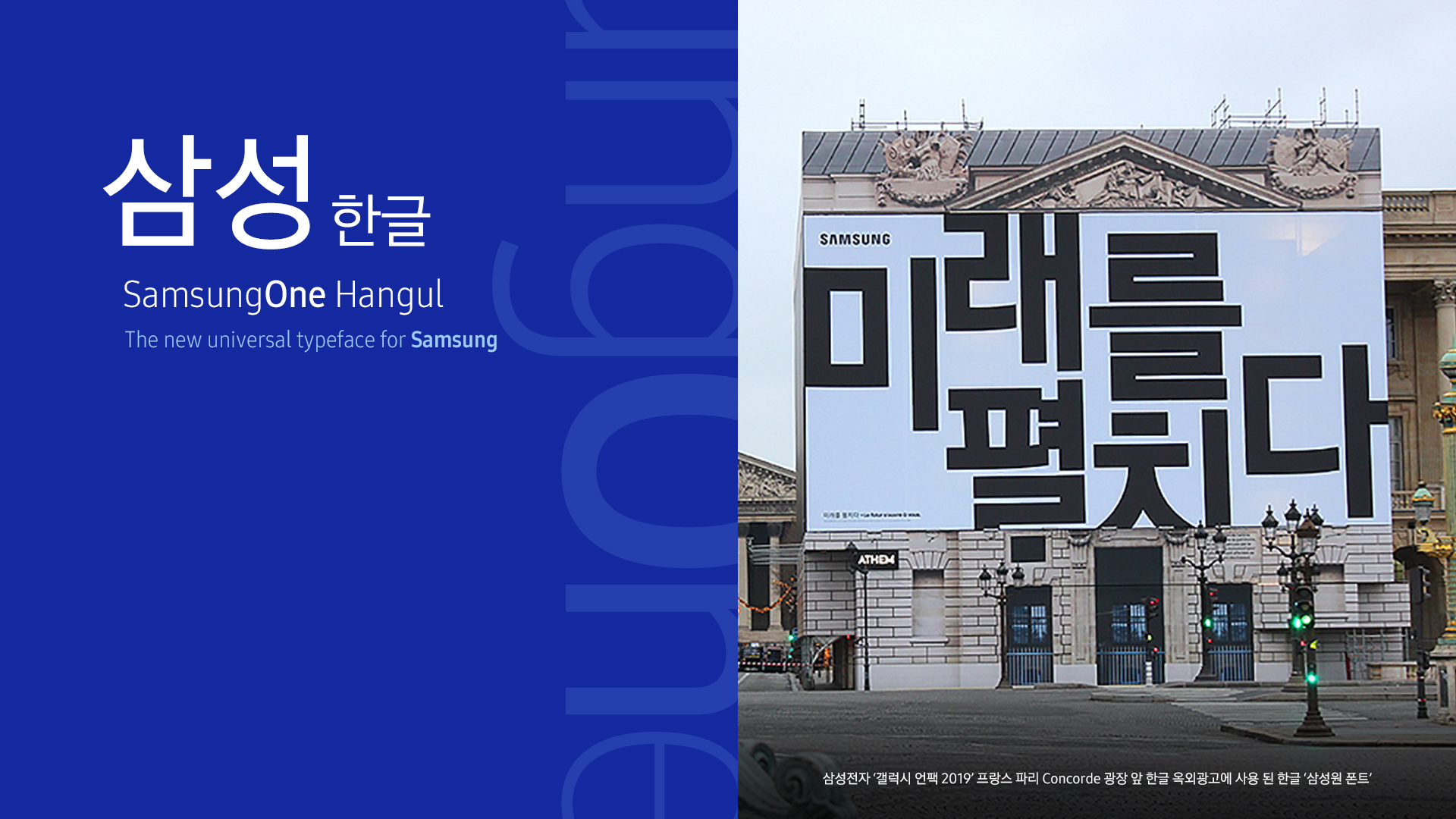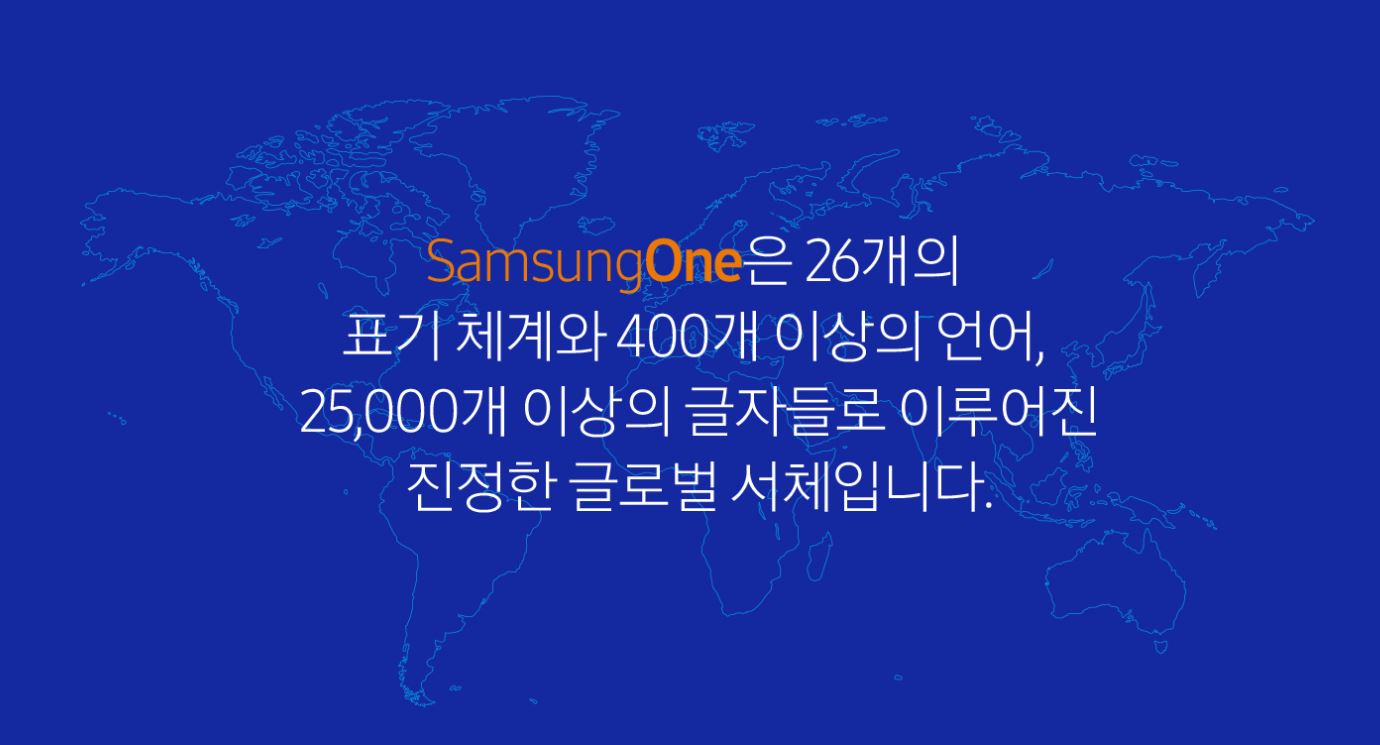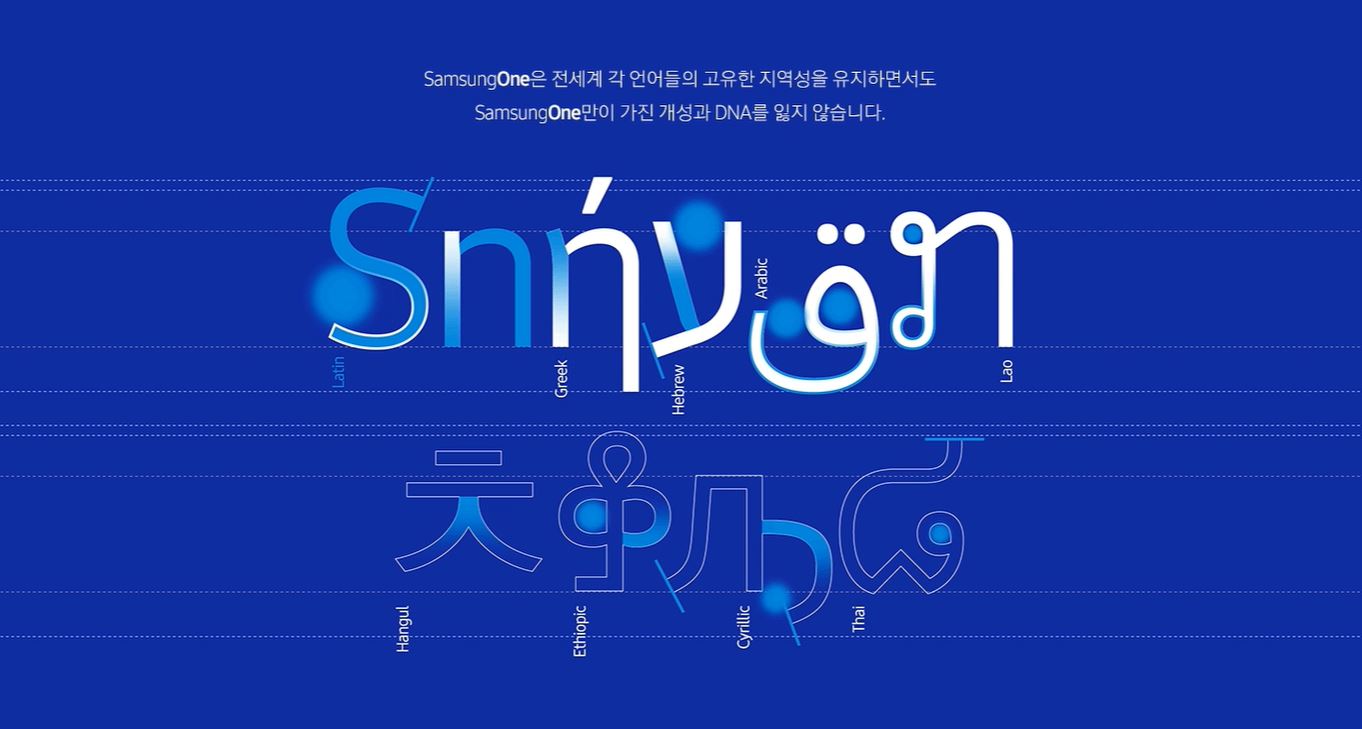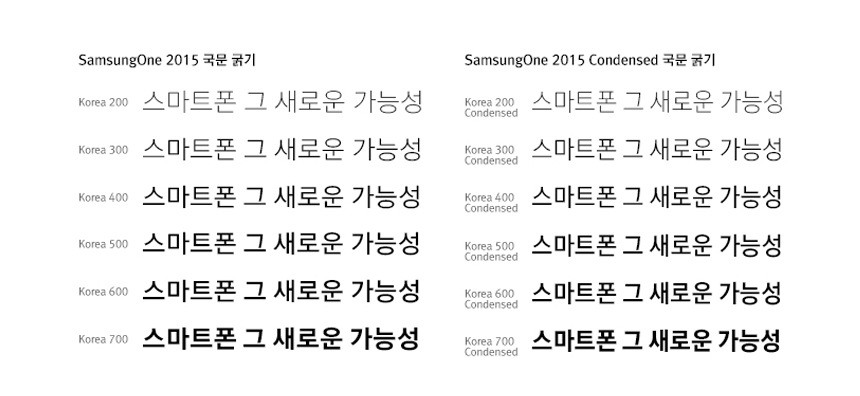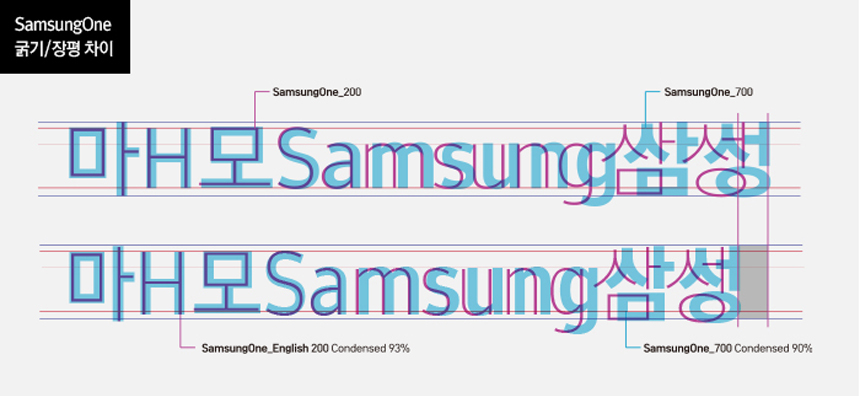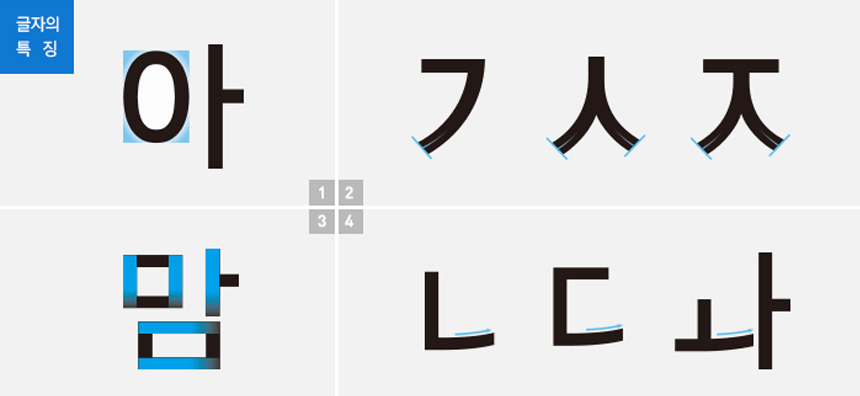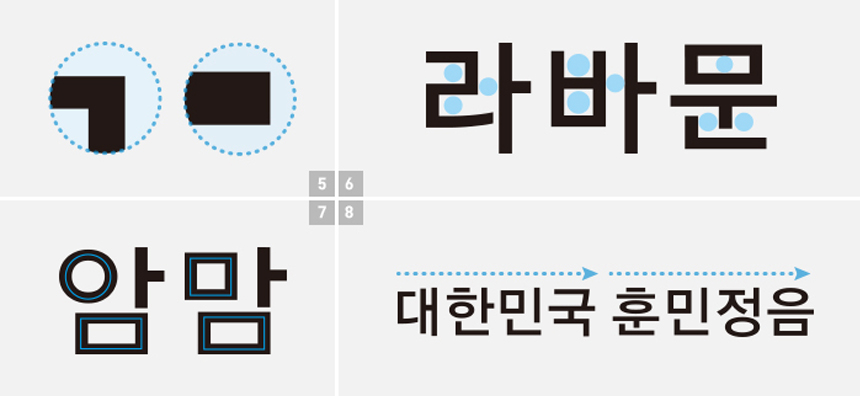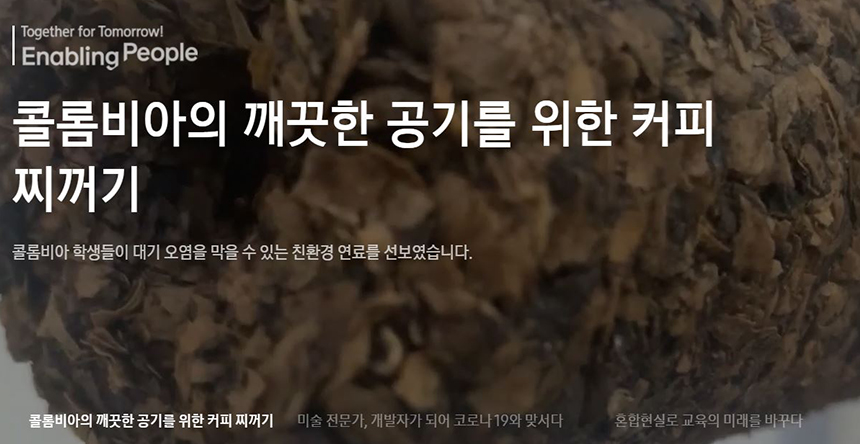
오늘 알아볼 전용서체는 대한민국을 대표하는 기업인 삼성의 전용서체 「SamsungOne」한글 입니다. 2015년부터 2018년까지 오랜 기간에 걸쳐 폰트릭스에서 개발한 삼성의 국문용 서체는 현재까지 삼성전자 전사 국문 폰트로 다양하게 사용되고 있습니다. 디스플레이, 인쇄물 등 모든 환경에서 최적화로 사용이 가능하도록 개발된 서체입니다.
글로벌 서체 SamsungOne
전용서체를 제작할 때 한글을 먼저 만드는 경우가 있고, 영문을 먼저 만든 후 그 컨셉에 맞춰 한글을 제작하는 경우가 있는데 삼성의 SamsungOneKorean 서체의 경우는 후자에 해당됩니다. 즉 영문은 해외 디자이너가 먼저 개발하고 한글은 거기에 맞춰 제작한 사례입니다. 영문의 경우 세계적인 타이포그래퍼이자 그래픽 디자이너인 네빌 브로디(Ceo, Brody Associates)가 제작하였습니다.
"중요한 것은 쓰여진 단어가 아니라 그것이 어떤 방식으로 쓰여졌느냐이다." - 네빌 브로디
'하나의 서체는 곧 하나의 시스템'이라고 말한 네빌 브로디는 수많은 제품과 플랫폼을 보유한 삼성전자를 대표하는 서체를 만들기 위해 고군분투했다고 하는데요. 특히 작은 스크린에서나 대형 옥외광고에서나 눈에 잘 띄어야 하기 때문에 스케일(크기)에 가장 중점을 두었고, 소문자 높이를 키워 가독성을 강화시킨 것이 특징입니다. 이러한 특징들이 국문 서체에서도 잘 드러나도록 디자인했습니다.
삼성원 한글 서체의 특징
SamsungOneKorean 서체는 200~900까지 총 8종(TTF/OTF)의 굵기로 파생되었고, 힌팅은 총 6종의 굵기로 파생되었습니다. Condensed(폭이 좁은)까지 제작을 진행했기 때문에 3년 이상의 긴 시간이 소요되었습니다. 국문 폰트를 담당한 박용락 디자이너는 그동안의 한글 고딕 제작 노하우를 모두 담았다고 해도 과언이 아니었다고 하는데요. 그 디테일들을 한 번 자세히 살펴보겠습니다.
활자의 완성도는 디테일에서 차이가 납니다. 글자 내 공간감을 주는 꽉 찬 곡선의 형태, 맺음 부분이 수적적인 자소, 시각적으로 같은 두께로 보이게 하는 굵기 처리, 그리고 곡선 처리가 미묘한 자소 등 세심하게 작업했습니다. 영문과 동일한 특징들을 적용해 영문, 한자와의 조화도 균형미 있게 제작되었습니다.
장식 없는 산세리프 형태로 깔끔한 이미지를 주고, 자소와 자소 사이의 간격이 균일하고 일정한 느낌을 주어 간결합니다. 한글 자음 'ㅇ', 'ㅁ'과 같이 원, 사각형으로도 보이는 기하학적인 형태를 담고 있으며, 대한민국 문서 체계에 맞게 왼쪽에서 오른쪽으로 흐르는 좌횡서 형식을 띄고 있습니다.
SamsungOne 폰트의 활용
SamsungOneKorean 서체는 삼성전자 홈페이지 및 여러 삼성의 웹사이트에서 다양하게 활용되고 있습니다. 용도에 맞게 적당한 굵기와 크기로 쓰여 높은 가독성과 함께 디스플레이에 최적화된 모습을 볼 수 있습니다.
사용성이 높은 본문형 고딕 서체이기 때문에 짧은 문구가 들어가는 광고든, 문장이 긴 콘텐츠든 여러 방면으로 활용하기에 좋습니다. 적절한 공간감을 통해 작은 글자는 서로 잘 구분되고, 큰 글자는 역동적인 느낌을 주어 임팩트 있게 표현됩니다.
기업전용서체 제작을 통해 기업의 아이덴티티와 심미성, 가독성 모두를 잡은 성공적인 브랜딩 사례입니다. 고객과의 커뮤니케이션을 중요시하며 끊임없이 고민하고 연구한 결과 완성도 높은 전용서체가 탄생했습니다. 기업전용서체는 브랜드의 정체성과 이미지, 서비스 등을 하나의 폰트를 통해 일체화함으로써 브랜드를 강화하고 소비자에게 신뢰감을 줄 수 있습니다.